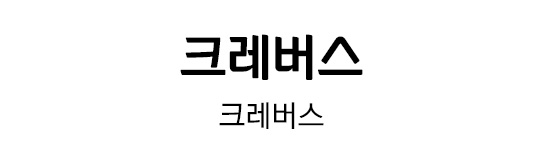
아는체(제목용) - 크레버스의 CI를 디자인에 접목하여 플레이 버튼의 삼각형이 연상되는 대칭형 ㅅ꼴과 부드럽게 이어지는 흘림이 특징인 제목용 서체입니다.
하는체(본문용) - 모던하고 가벼운 탈네모꼴 골격이 큰 특징이며, 시원하게 뻗은 직선 획으로 진취성을 담은 본문용 서체입니다.
| 프로젝트명 | 크레버스 전용서체 '아는체', '하는체' |
| 스펙 | 한글 11,172자 / 영문 94자 / 약물 986자 |